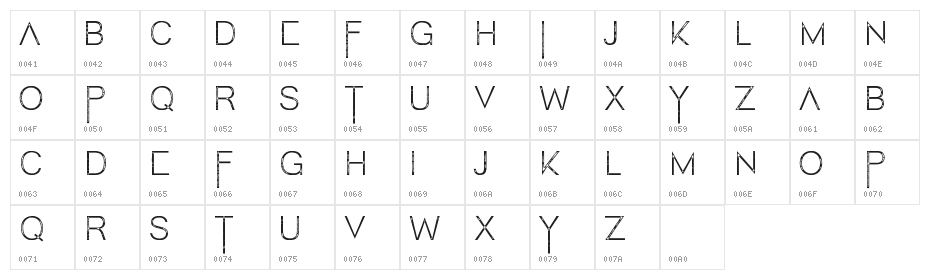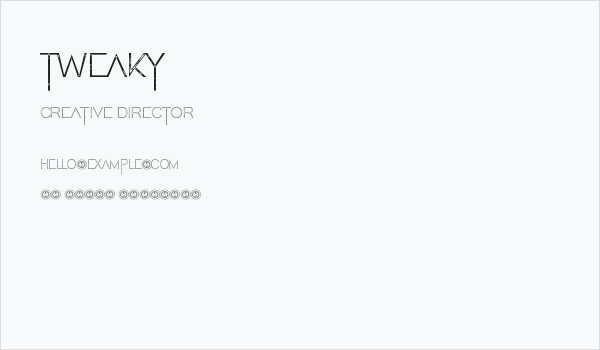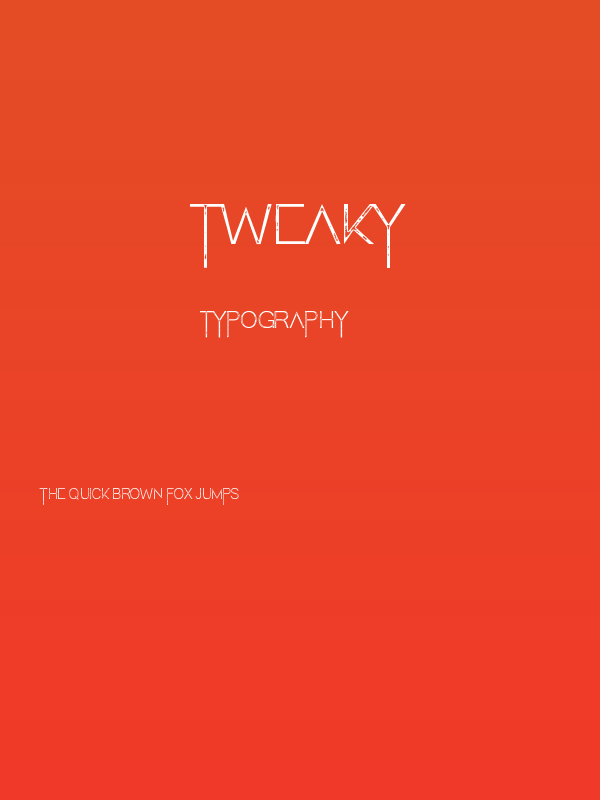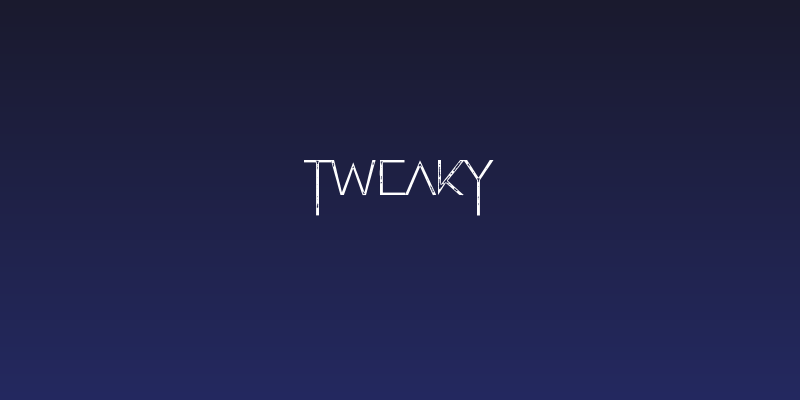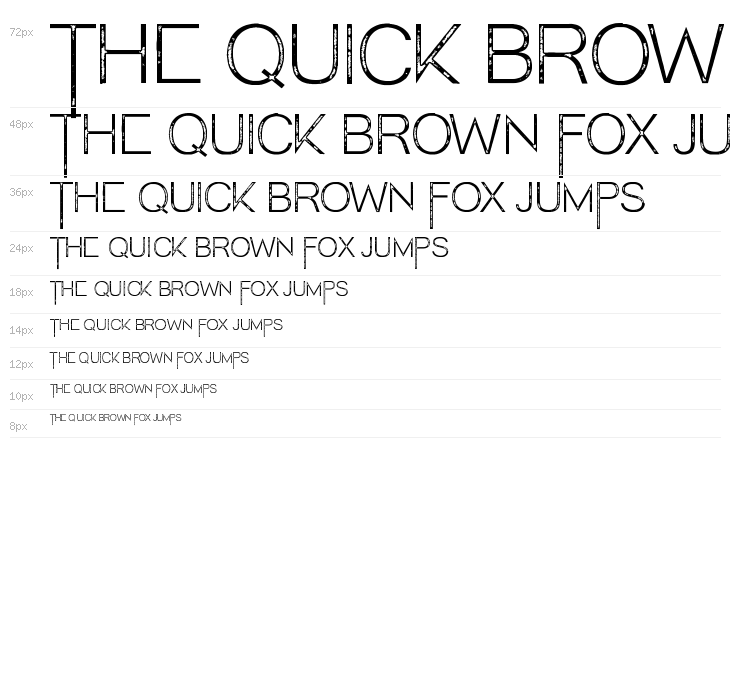
Tweaky Font
✎ Distorted Eroded
Fonts by Chris Vile
| おすすめプロジェクト | Ideal for projects requiring a vintage or industrial aesthetic, such as posters, album covers, or branding for artisanal products. |